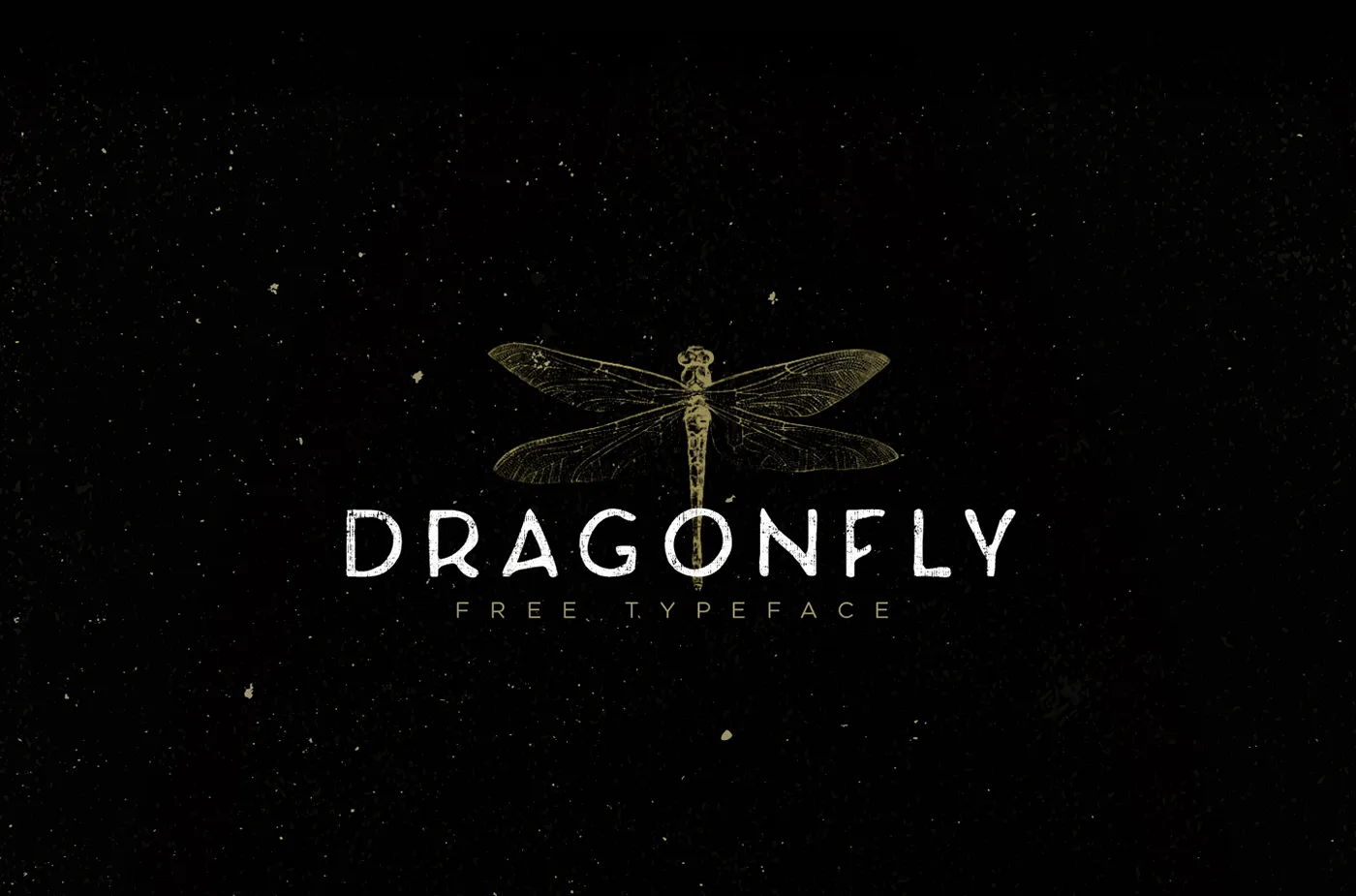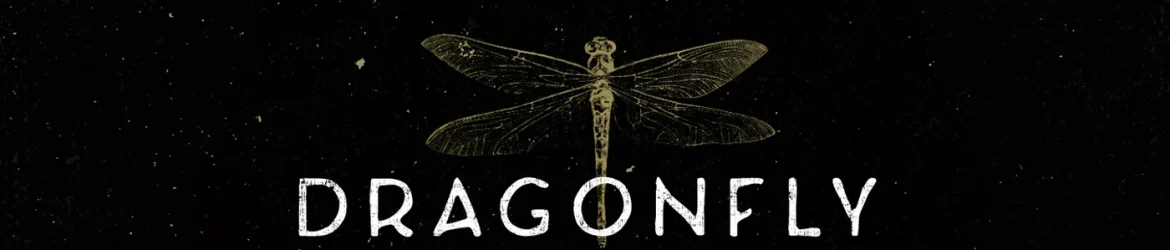
A Dragonfly Typeface é uma fonte de categoria Playful, criada pelo designer Hamilton, que traz elementos que lembram as dançantes aranhas dragonflies. Esta fonte não só oferece um toque fresco e divertido para aplicativos digitais como websites ou materiais impressos, mas também adiciona um brilho único aos seus projetos. A personalidade da Dragonfly Typeface é tão vibrante quanto a essência das danças dos dragões-flutteries. Suas linhas fluidas e elegantes garantem uma transição natural entre as palavras e o espaço entre elas, tornando-a perfeita para gráficos de blog ou páginas da web que desejam destacar-se em um ambiente digital. Adotada por designers que queriam algo diferente e alegre no design do seu projeto, esta fonte é ideal para qualquer aplicação que deseje uma aparência leve e divertida. Se você está buscando uma alternativa àqueles estilos mais sérios e quase sempre tradicionais, a Dragonfly Typeface pode ser sua perfeita opção. Incorporar o brilho da Dragonfly Typeface em seus projetos digitais certamente será um sucesso, já que não há dúvida de que este é um recurso gráfico amigável para os olhos que irá chamar a atenção. É uma fonte leve e alegre ideal para qualquer projeto que deseja um toque animado sem sacrificar qualidade ou estilo.